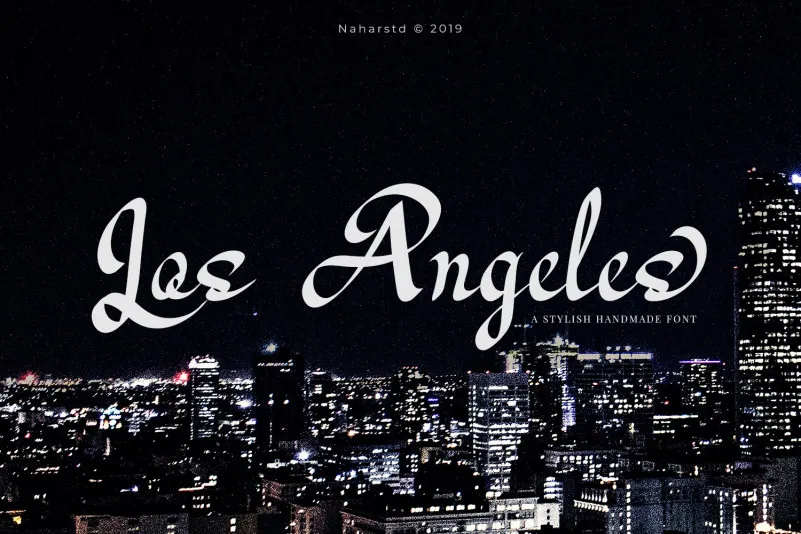
Los Angeles – Modern Script Font – Download Grátis
A Los Angeles – Modern Script Font é uma elegante fonte feita à mão que se adequa a diversos projetos criativos. Desenvolvida para designers e profissionais do design, esta fonte moderna e versátil pode ser usada tanto no desenvolvimento de logotipos quanto em projetos de marca. Sujeitando-se a designs de mobília, embalagens de produtos, tigelas, citações, panfletos, sacolas de shopping, camisetas, capas de livros, cartões de nome, convites e cartas de aniversário, etiquetas e até mesmo em gravações especiais para eventos. Não importa qual projeto de design delicado que você esteja trabalhando, a Los Angeles – Modern Script Font traz um toque especial à sua obra, permitindo ao designer expressar individualmente o seu estilo personalizado. A fonte foi criada pelo designer Naharstd e pertence à categoria de Brush Fonts. Através do uso desta fonte moderna, você pode adicionar um toque único e autêntico a qualquer projeto, oferecendo uma experiência visual única que cativa o olhar da sua audiência. Numa era cada vez mais digital, essa mão-de-obra criativa oferece uma maneira poderosa de tornar as experiências digitais em algo que você pode realmente tocar e sentir – desde os títulos de filmes até as bordas dos seus próprios produtos em embalagens ou prateleiras.